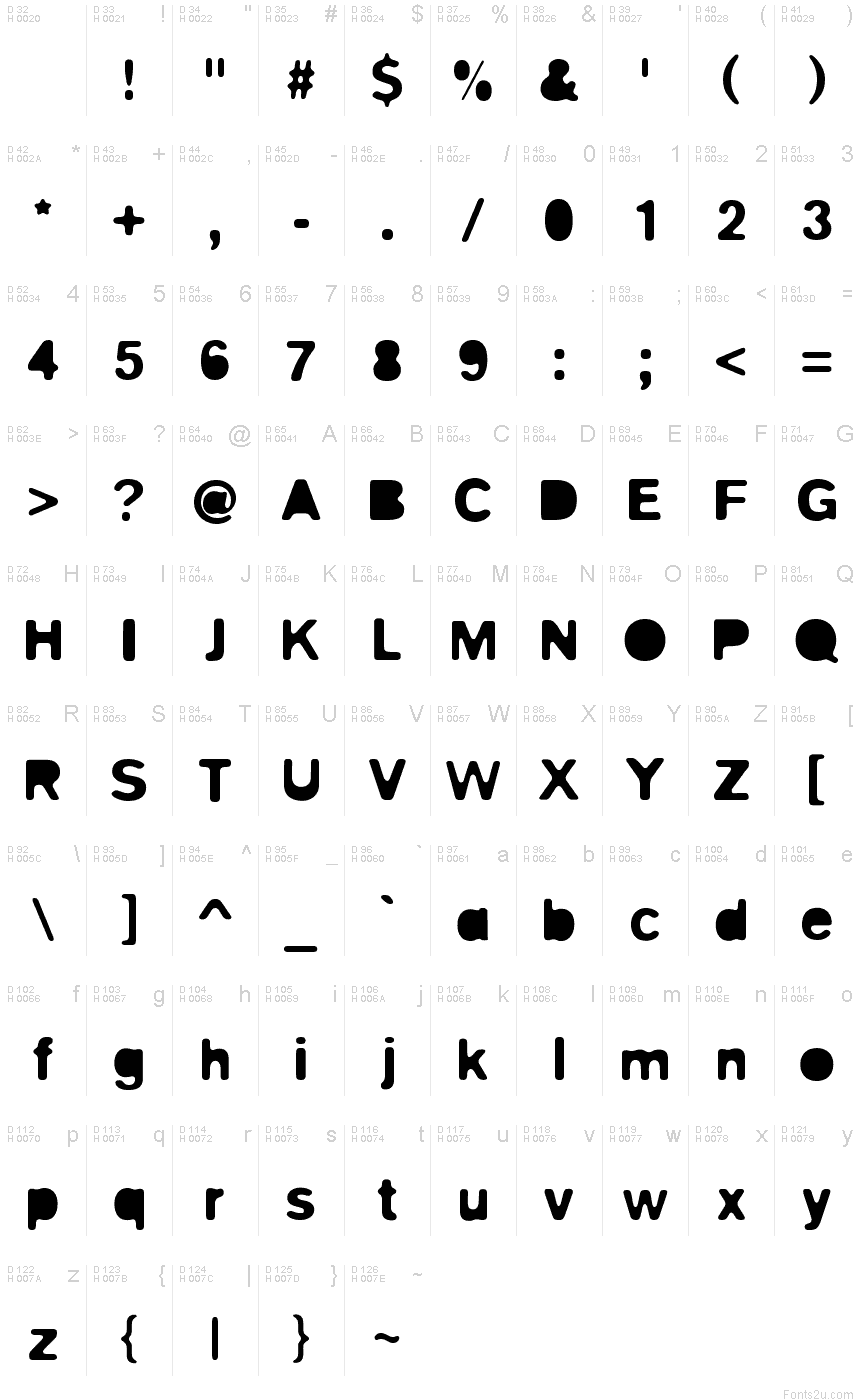
Biliz Blur Regular je bezplatné, zaoblené a deformované titulkové písmo s měkkým, „nafouklým“ rytmem, který působí jako něco mezi bublinovým písmem a logotypem taveným teplem. Písmena jsou masivní a kompaktní, s tupými rohy, výrazným vyhlazením a lehce rozmazanou siluetou, díky čemuž slova působí, jako by byla spíše odlita než vykreslena.
Díky tomu je přirozenou volbou pro hudební plakáty, streetwear branding, samolepky, titulky a krátké texty, kde chcete dosáhnout výrazného tvaru místo ostrých detailů. Jakožto font zdarma se hodí i pro loga, popisky na obalech a rychlé hlavičky na sociálních sítích, protože nafouklé křivky dodávají i krátkým slovům odvážný, hmatatelný objem.
Písmo upravené podle Nevillea Brodyho.